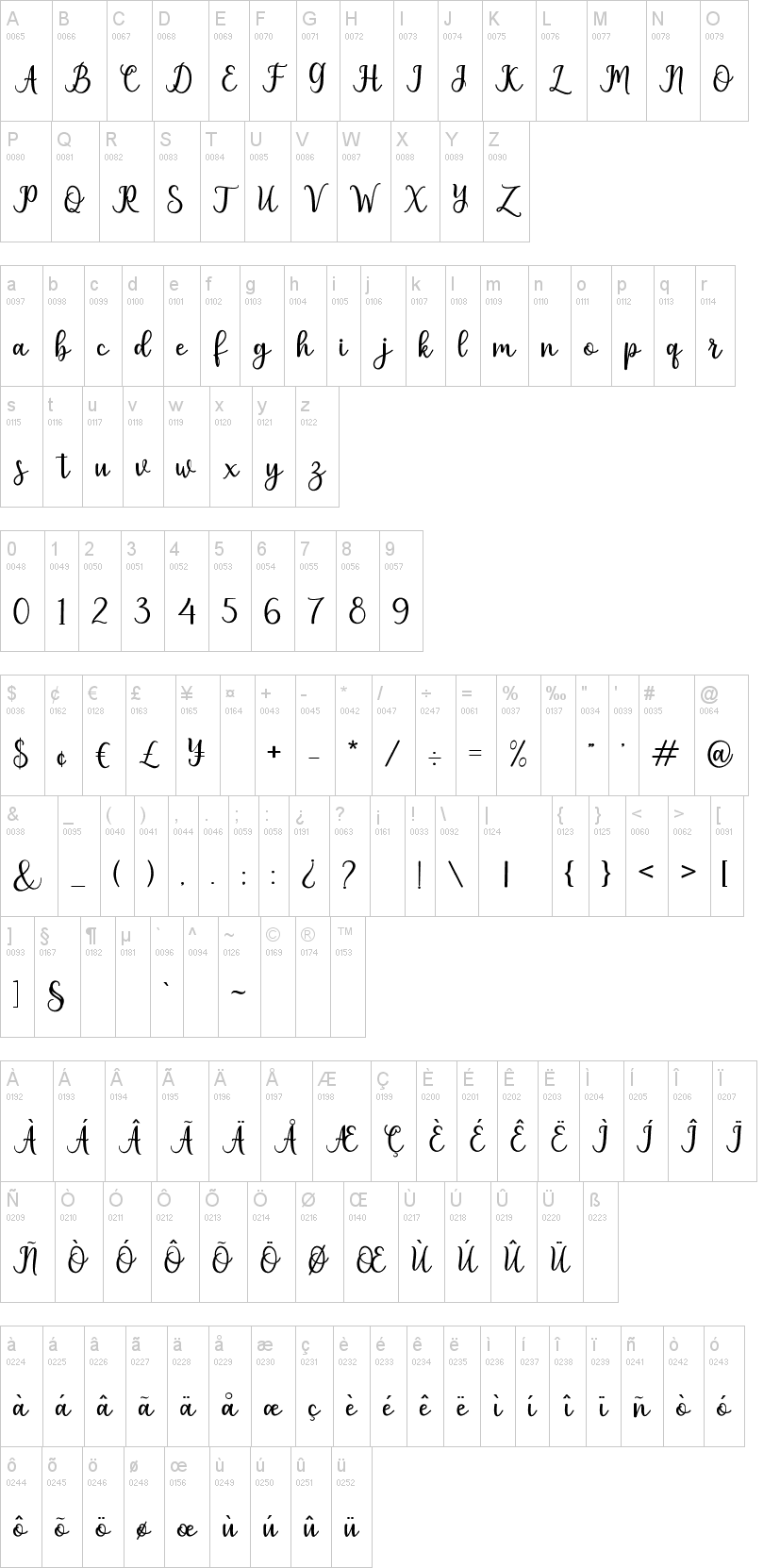
Pruistin
Pruistin 是一种现代简洁的屏幕字体,由美国设计师 Alex Kaczun 于 2008 年开发。Pruistin 字体的特点是笔画细腻,结构清晰,给人以简洁、清新的感觉,是一种非常适合用于网页设计的字体。Pruistin 字体可以用于多种类型的文本,包括网页标题、文章标题、段落文字等,可以提供一种简洁而又大气的视觉效果。
Pruistin是一款非常不错的手写艺术字体,具有很好的视觉感,适合于文化类的宣传设计、商业类品牌的广告和产品包装设计以及个性化文字排版等较多场景。
Pruistin字符映射图